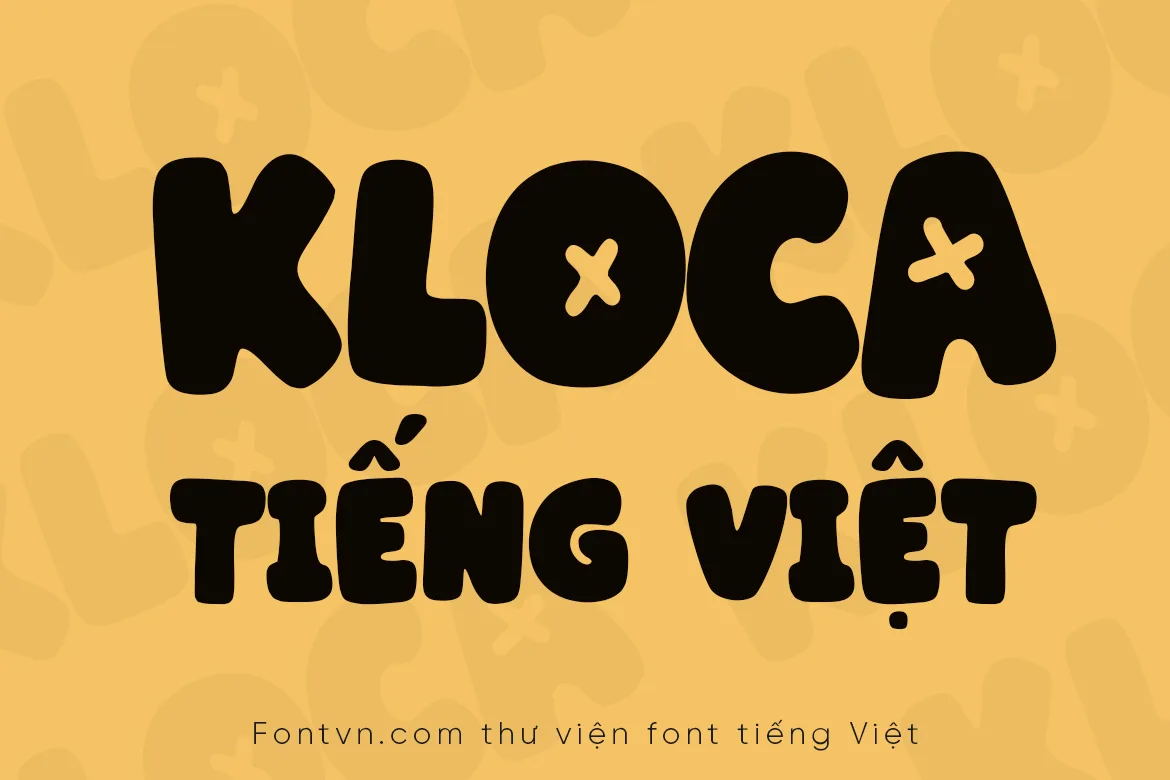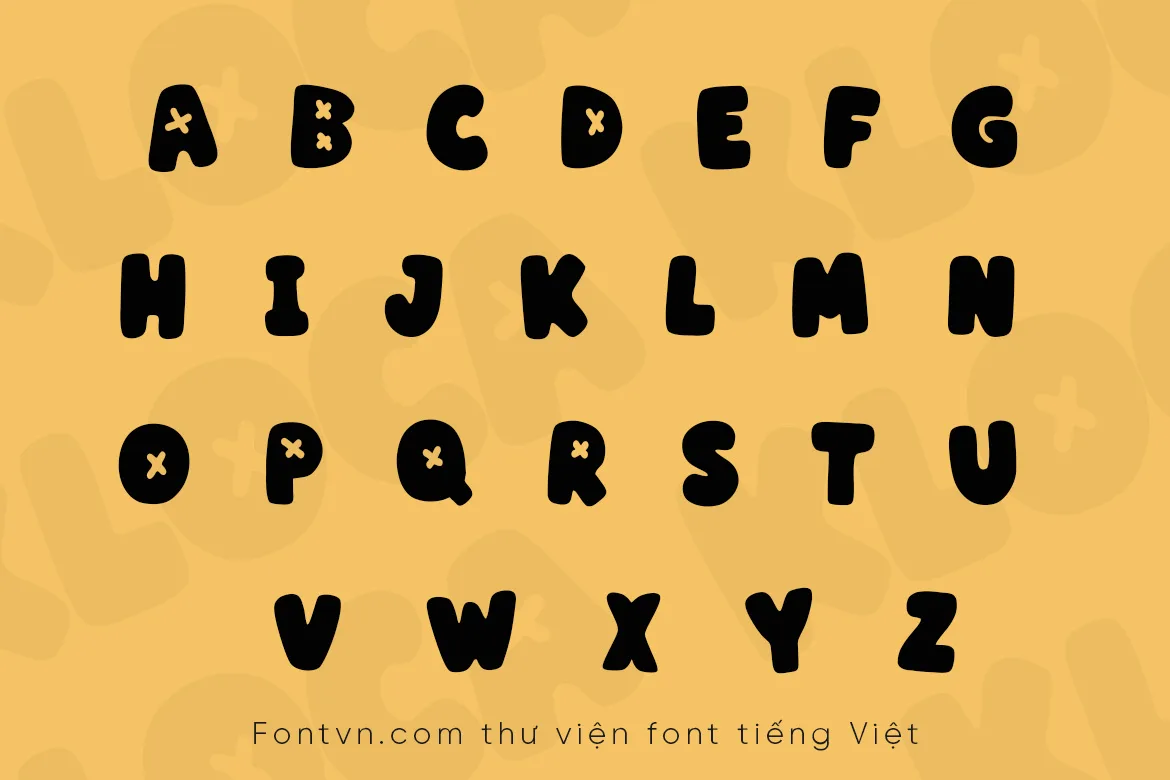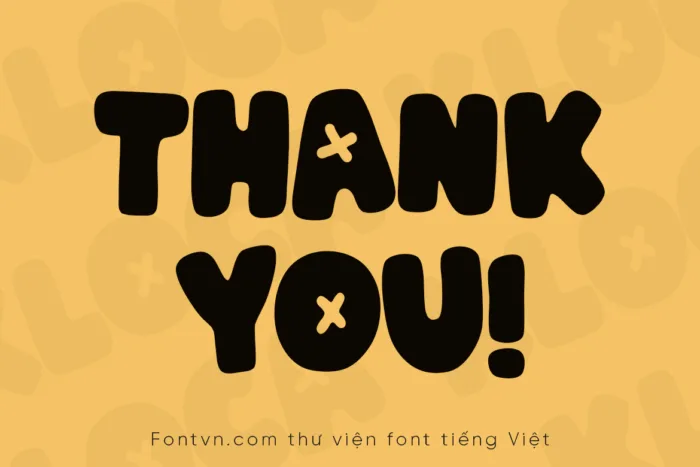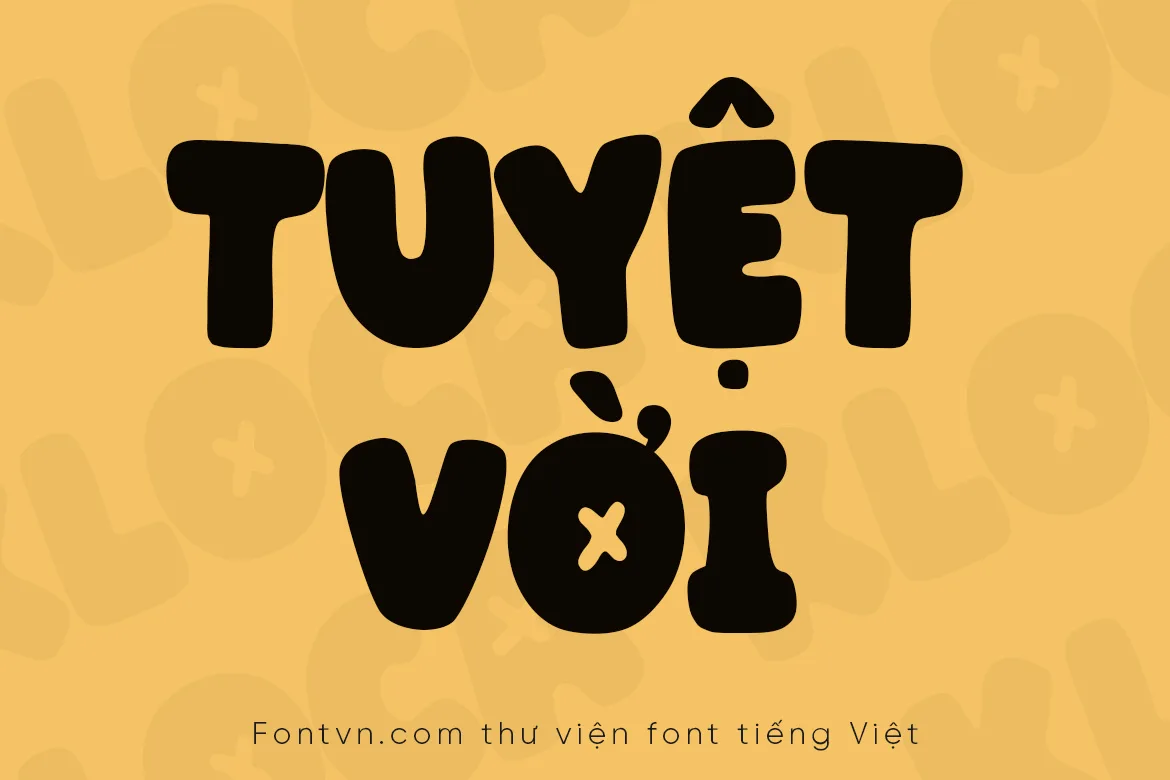
DVN KLOCA tiếng Việt – Font Phá Cách & Tràn Đầy Năng Lượng
Chào mừng bạn đến với thế giới đầy màu sắc của KLOKA – một phông chữ hiển thị (display font) mang đậm tinh thần vui tươi và sáng tạo. Với những đường nét dày dặn, bo tròn mềm mại cùng điểm nhấn dấu ‘x’ tinh nghịch ẩn mình bên trong các con chữ, KLOKA không chỉ là một phông chữ mà còn là những nhân vật hoạt hình đang mỉm cười trên thiết kế của bạn. Phông chữ này hỗ trợ đầy đủ tiếng Việt, là sự lựa chọn hoàn hảo để thổi bùng sức sống cho các ấn phẩm thiếu nhi, bìa sách, bao bì đồ chơi, logo thương hiệu mẹ & bé, hay bất kỳ thiết kế nào cần một chút gia vị của sự vui vẻ và lạc quan.